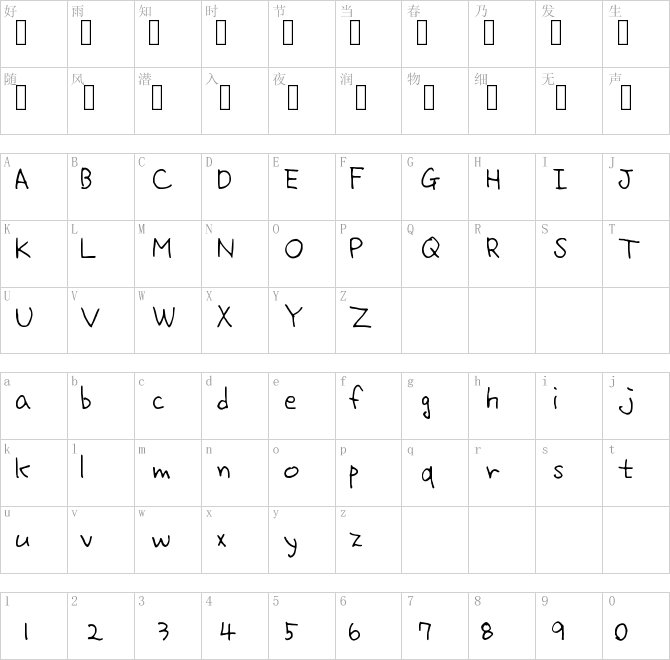
나눔손글씨 아인맘 손글씨韩国字体
나눔손글씨 아인맘 손글씨韩国字体,这款字体结构工整、笔画清晰,兼顾美观与易读性,适用于标题、正文、海报、包装、LOGO 等多种场景。字形优雅稳定,风格百搭耐看,适配日常排版与创意设计,让文字呈现更舒适、更具质感。나눔손글씨 아인맘 손글씨韩国字体一笔一画,皆是细节,以均衡的比例、流畅的线条打造舒适视觉体验,字形端正大气,风格简约现代。无论是商业设计、品牌宣传还是日常排版,都能轻松驾驭,让文字更有格调与力量。나눔손글씨 아인맘 손글씨韩国字体字体下载。
• 字体名称:나눔손글씨 아인맘 손글씨
• 字体风格:Regular
• 字体标识:CLOVA OCR : Nanum AInMamSonGeurSsi
• 字体全称:나눔손글씨 아인맘 손글씨